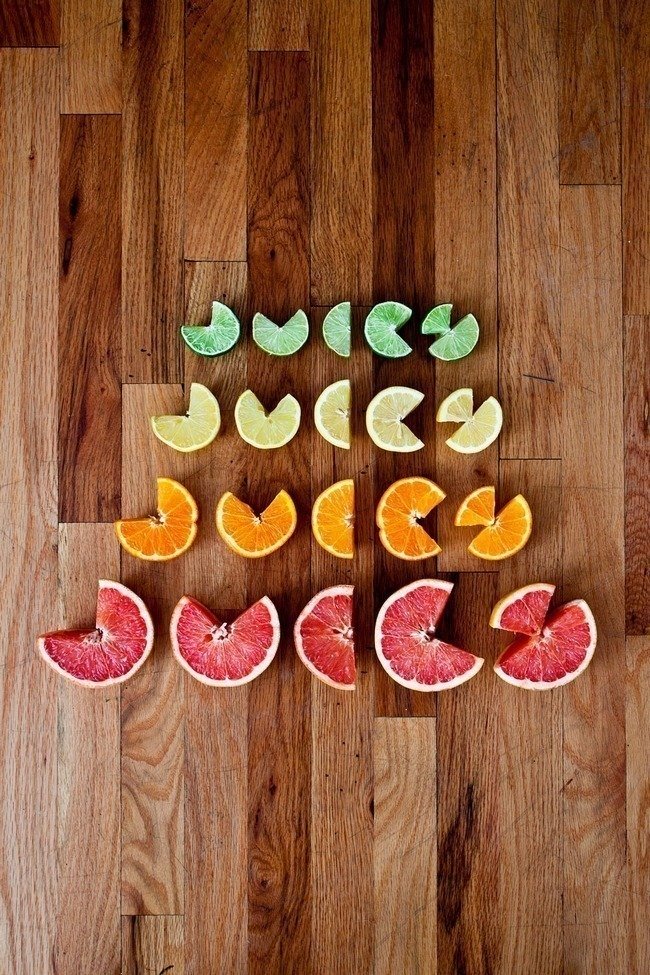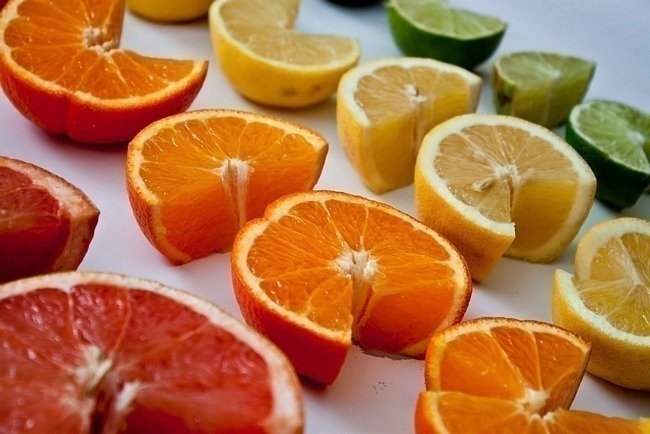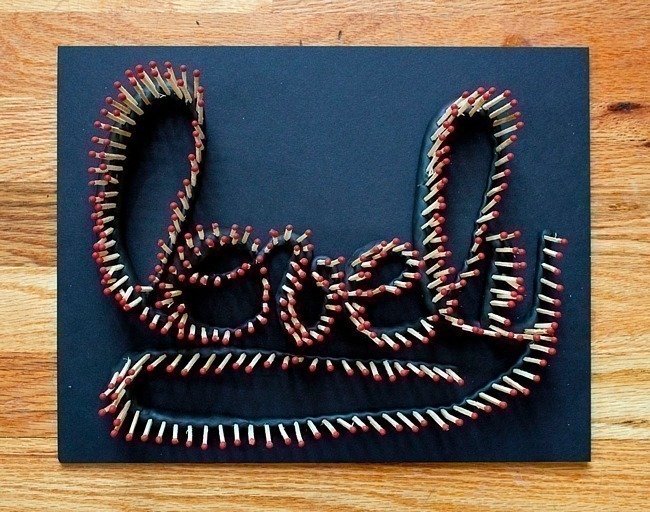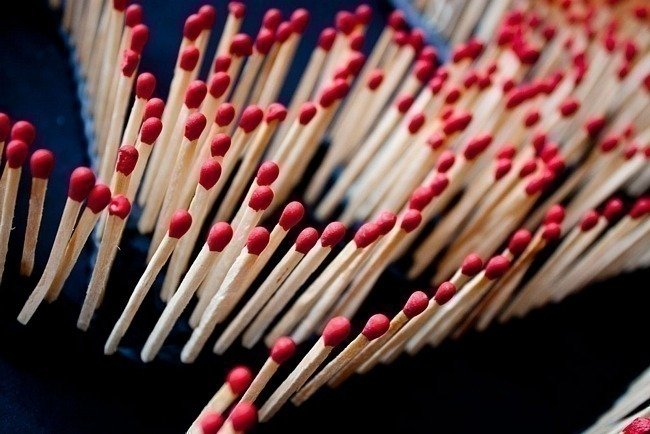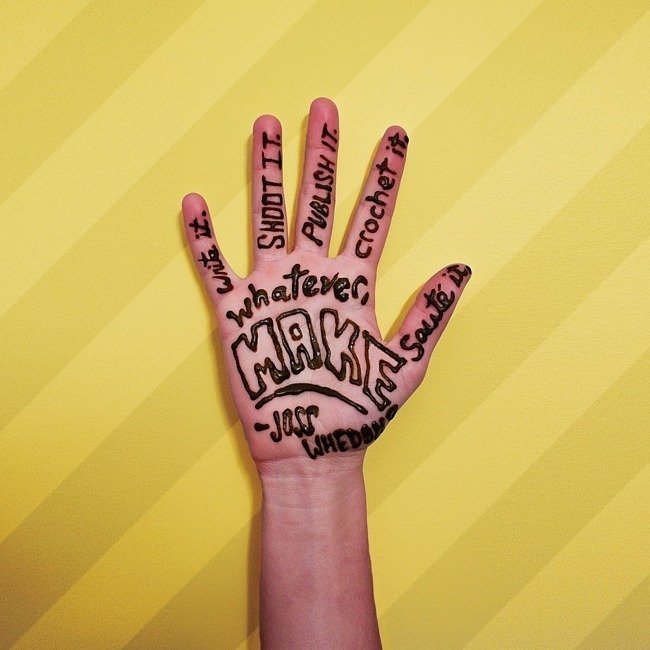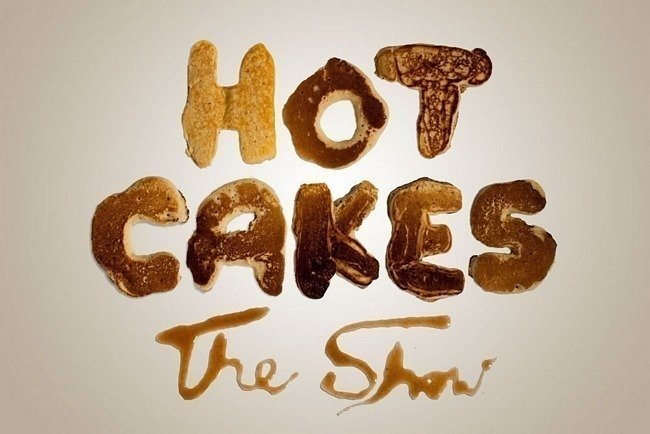
O Designer Nova Iorquino Allisson Supron montou um projeto chamado “Play” que idealiza a criação de diversas tipografias através do processo criativo experimental.
Nas peças, que também propõem o desvio do mundo virtual, são misturadas diversas cores e materiais (como tábuas de carne, botões e palitos de fósforo) em conjunto com técnicas nada convencionais a fim de trabalhar o estímulo criativo, sem a obrigatoriedade de um computador.